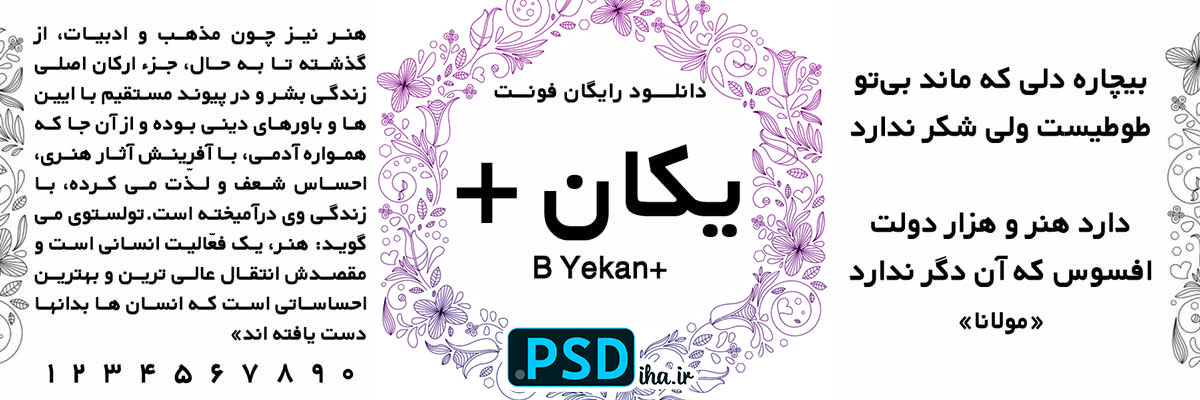
فونت فارسی یکان پلاس
فونت فارسی یکان+ پلاس
اگه جزو اون دسته از طراحان یا مدیران کسب‌وکاری هستید که هر روز با انبوهی از اوراق اداری، فرم‌های پرکاربرد، صورت‌حساب‌ها و قراردادها سر و کار دارید – حتماً می‌دونید که انتخاب فونت اشتباه چقدر می‌تونه تمرکز رو به هم بزنه و خستگی بصری بیاره. فونت فارسی یکان دقیقاً برای همینه که ساخته شده: خونایی بی‌نقص در حجم بالا، ظاهر رسمی و در عین حال مدرن، و فاصله‌گذاری استاندارد که چشم توی متن گم نشه.
من خودم توی طراحی صدها قالب اوراق اداری تو پی اس دی ها، از فرم‌های پرسنلی گرفته تا سربرگ‌های سازمانی و فاکتورهای فروش، فقط و فقط از یکان استفاده می‌کنم. دلیلش سادست: این فونت حتی توی سایزهای ریز ۹ یا ۱۰ پیکسل هم لبه‌هاش صاف می‌مونه و هیچ حرفی به حرف دیگه نمی‌چسبه. برای چاپ روی کاغذهای معمولی اداری (اون مدل کاغذهای نازک و سفید که نور از پشتشون می‌اد) معجزه می‌کنه – جوهر نمی‌ریزه، حروف خرد نمی‌شن و کل متن یه دست به نظر می‌رسه.
چرا فونت فارسی یکان استاندارد طلایی اوراق اداری شماست؟
اولاً، طراحی منظم و بی‌حاشیه‌اش باعث می‌شه توی تیترها (مثل عنوان قرارداد یا لوگوی شرکت) رسمی و قدرتمند دیده بشه، توی متن‌های بلند (مثل بندهای حقوقی) بدون خستگی چشم خونده بشه و توی پانویس‌ها یا جدول‌های اعداد (مثل فاکتورها) کاملاً شفاف و بدون خطا باقی بمونه. دوماً، با همه نرم‌افزارهای استاندارد مثل ورد، ایلاستریتور و پی دی اف سازها کاملاً سازگاره – چیزی بدتر از این نیست که فونت رو بفرستی برای چاپ، برات تبدیل به فرمت دیگه بشه و حروف به هم بریزه. با یکان، این اتفاق نمی‌افته.
کاربردهای حرفه‌ای فونت یکان توی کسب‌وکار شما:
• سربرگ شرکت‌ها و سازمان‌ها (لوگو + اطلاعات تماس با یکان رسمی و شیک درمیاد)
• صورت‌حساب و فاکتور فروش (اعداد کاملاً جداسازی شده، کوچک و بزرگ خوانا)
• قراردادهای کاری، فرم‌های استخدامی و بخشنامه‌های داخلی
• برچسب‌های اداری روی پوشه‌ها، لیبل محصولات رسمی و کاتالوگ‌های B2B